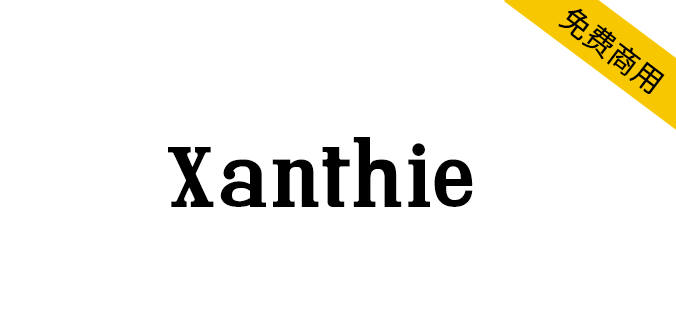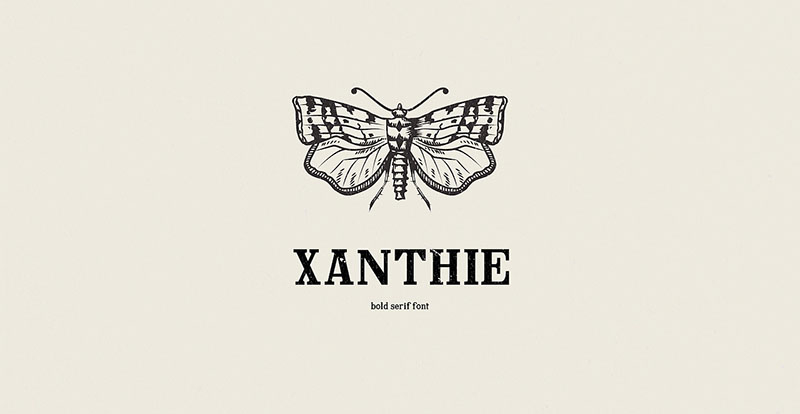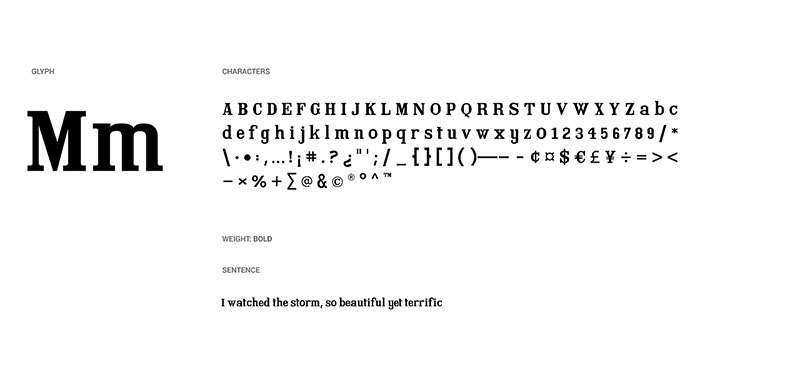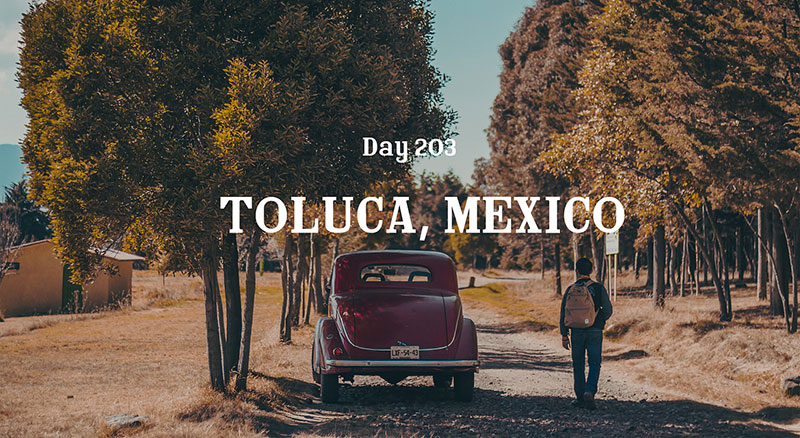
Xanthie是一种衬线字体,有怀旧的感觉。它的灵感来源于一本面向儿童的公共领域经典法语字母学习书。Xanthie是一种特别适合需要大标题的设计的字体。
字体名称:Xanthie
重量:粗体
设计:Simo Herold
Xanthie is a serif font with a nostalgic feel. It is inspired by a public domain vintage French alphabet learning book for children. Xanthie is a font suitable especially for designs needing big headings.
Font Name: Xanthie
Weight: Bold
Designed by: Simo Herold